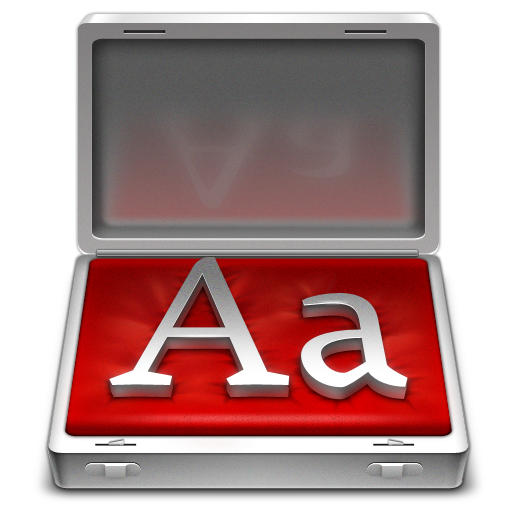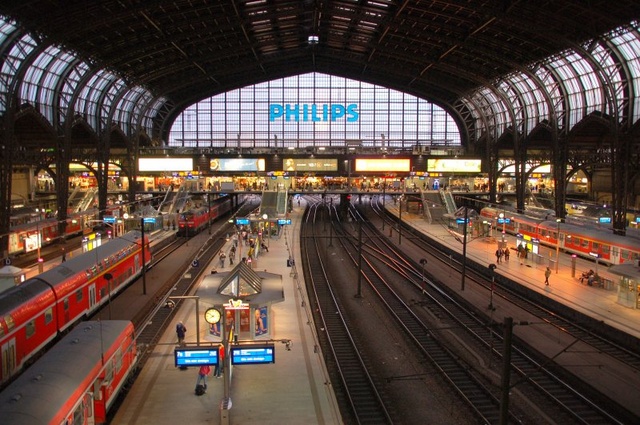
Welsche Schrift? Köln - Fontcase - Philips
vielleicht ist das ein unkonventioneller Beitrag, aber ich suche gleich drei Dinge auf einmal.
1. Ich war letzt Woche in Köln und mir ist aufgefallen, dass die Stadt ein sehr schönes
Erscheinungsbild hat. Weiß jemand, welche Schrift das ist?
2. Ich nutzte seit einigen Wochen Fontcase von Bohemian Coding und hatte mich gefragt, welche
Schriftart genutzt wird für das Aa im Logo? Ich hab BC kontaktiert und in der Antwort stand, dass
man sich selber nicht sicher sei, aber es viellicht die FF Absara ist. Die ist aber meines Erachtens
nicht. Weiß jemand zufällig welche das sein könnte?
3. Ich fahre täglich mit der Bahn nach Hamburg und sehe täglich die riesige Philips Werbung:
Das ist jetzt leider noch ein altes Bild. Mittlerweile wurde das Logo aktualisiert:
Ich finde, dass einer sehr schöne und gut gelungene Anpassung ist, weiß jemand zufällig, wer dafür
zuständig war?
1. Am Ende ist es immer Gerard Unger
3. Ah, aber viel findet man nicht darüber.
2. Ich nutzte seit einigen Wochen Fontcase von Bohemian Coding und hatte mich gefragt, welche
Schriftart genutzt wird für das Aa im Logo? … Weiß jemand zufällig welche das sein könnte?
Das ist die Agendatype von Fontfarm (siehe auch Artikel »Font Management with Fontcase, January 2009«).